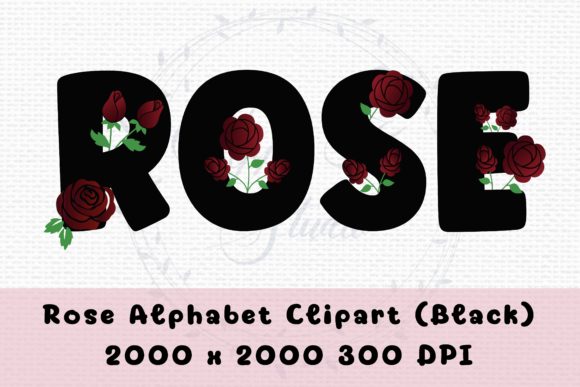
Red Rose Alphabet Clipart
Trouver les bons éléments de conception peut être un défi, mais Red Rose Alphabet Clipart propose une collection exceptionnelle qui rehausse instantanément votre travail.
Conçu avec précision, Red Rose Alphabet Clipart offre des vecteurs nets, une typographie fluide et une licence commerciale pour une tranquillité d'esprit.
Que vous créiez des produits POD (impression à la demande), des invitations de mariage ou des visuels pour les réseaux sociaux, Red Rose Alphabet Clipart est un choix idéal.